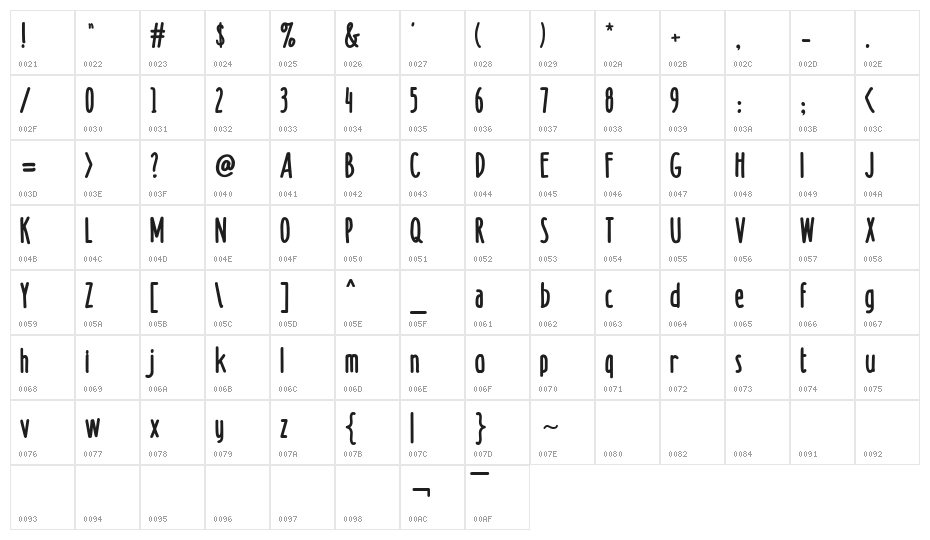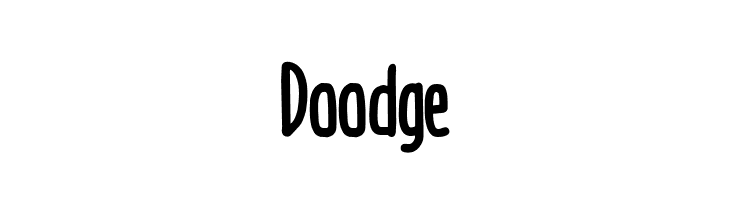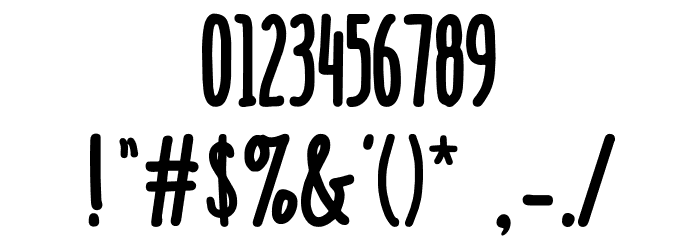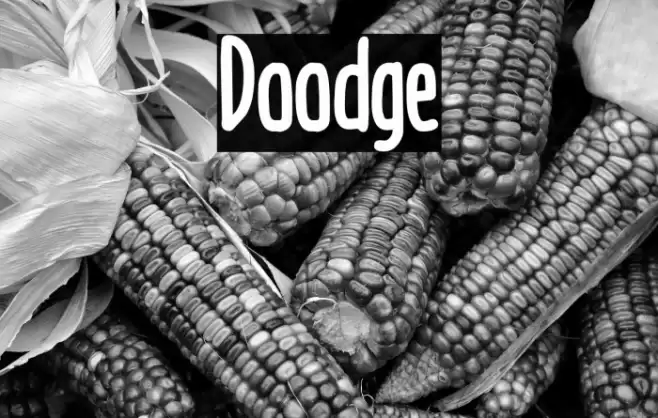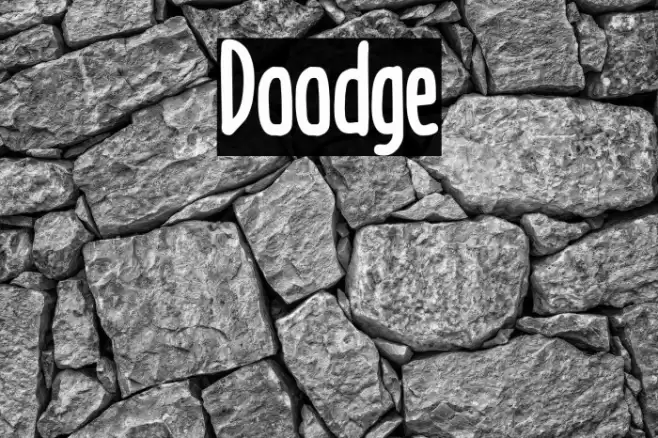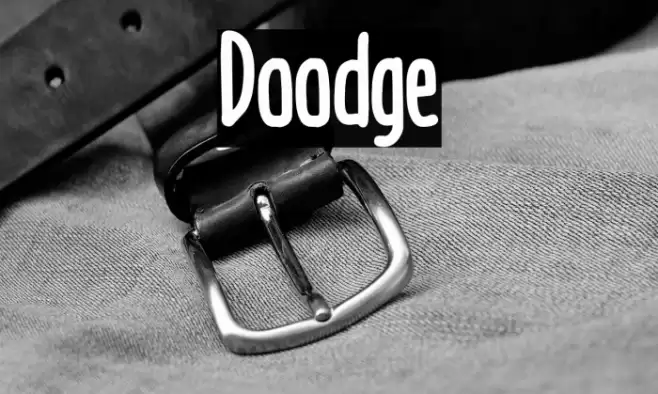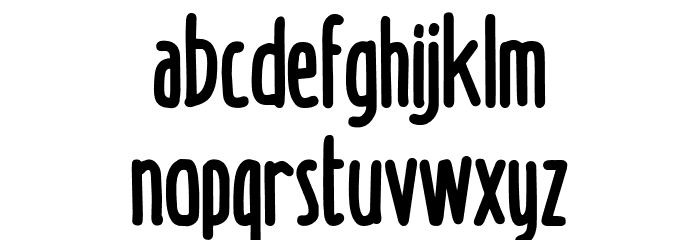
Doodge Font
| Gesamtstil | Playful |
| Vorgeschlagene Projekte | Ideal for children's books, greeting cards, playful branding, and social media graphics. |